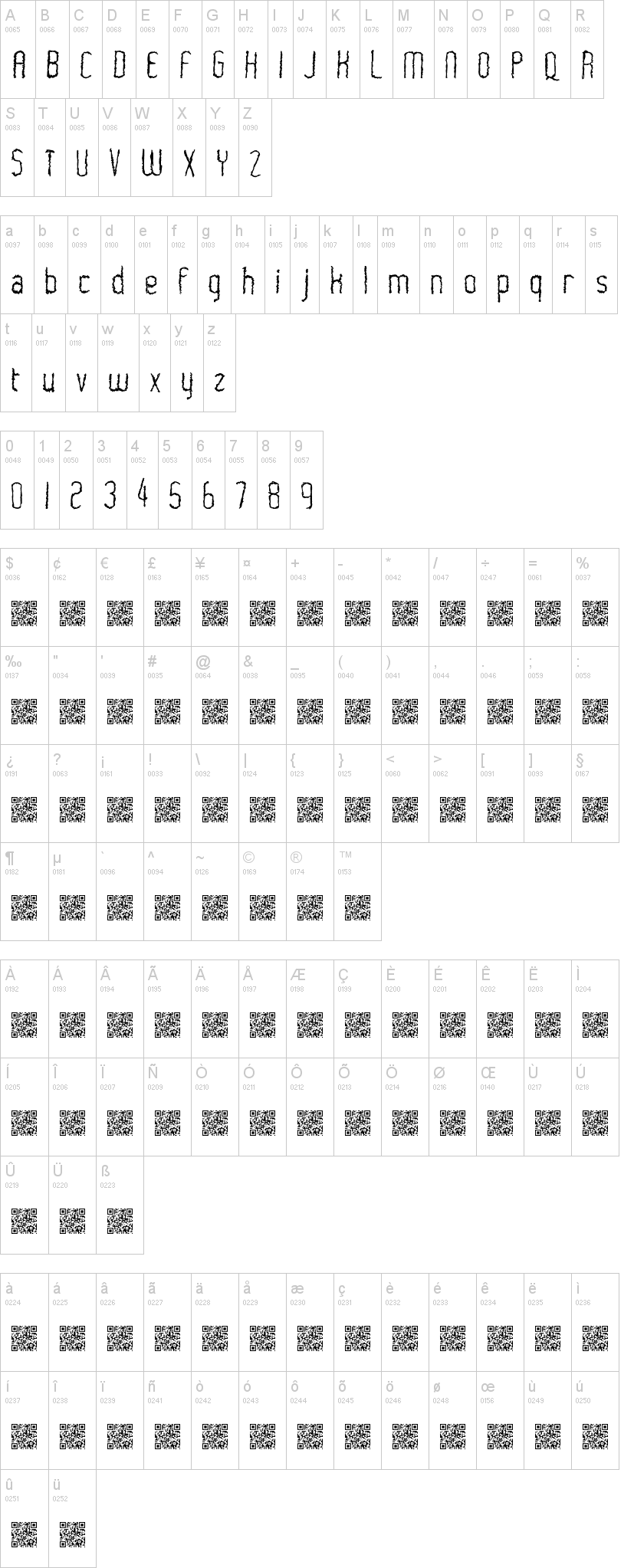
World Shocker
World Shocker 是一款显示字体,由美国设计师 Jesse Ragan 创作,于2019年发行。这款字体具有强烈的线条感和复古风格,可以用来创作视觉效果,也可以用于文字排版。它有着清晰的空间感,可以使文字更加清晰突出,从而让文字内容更加易读。此外,它还拥有多种字体风格,可以满足不同设计的需求。
World Shocker是一款非常不错的手写艺术字体,具有很好的视觉感,适合于文化类的宣传设计、商业类品牌的广告和产品包装设计以及个性化文字排版等较多场景。